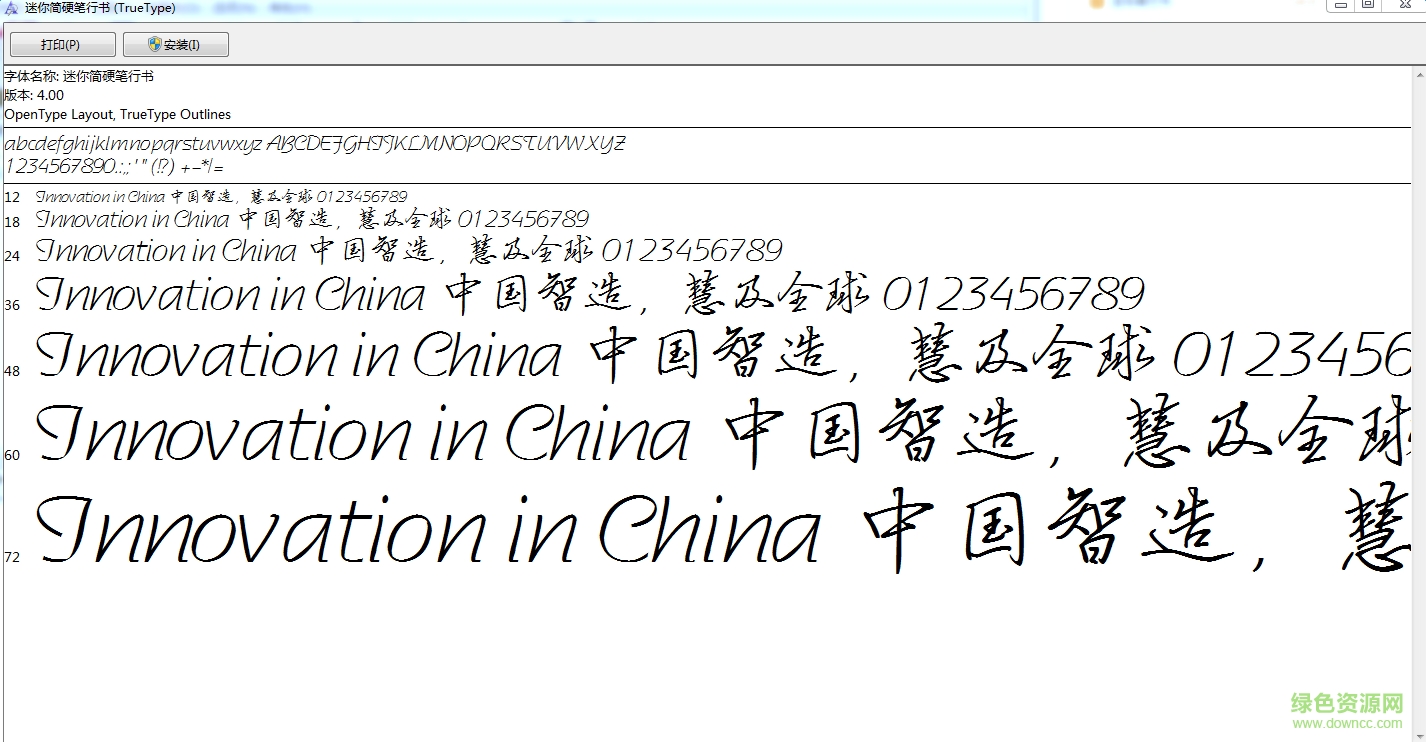
迷你簡(jiǎn)硬筆行書字體是一款行書類字體軟件,其飄逸隨性的風(fēng)格,讓文字栩栩如生,給人一種飛翔的既視感,非常好看,感興趣的朋友歡迎來(lái)綠色資源網(wǎng)體驗(yàn),還有更多字體等你下載哦!
迷你簡(jiǎn)硬筆行書是在楷書的基礎(chǔ)上發(fā)展起源的,介于楷書、草書之間的一種字體,是為了彌補(bǔ)楷書的書寫速度太慢和草書的難于辨認(rèn)而產(chǎn)生的。
字體雋秀工整,結(jié)構(gòu)狹長(zhǎng),字間距較大,排印清晰,整齊
劃一,適用于書籍、報(bào)刊、雜志的標(biāo)題字。
字形見(jiàn)方,結(jié)構(gòu)飽滿,筆法新穎雅致,具有獨(dú)特的藝術(shù)效
果。適用于書籍、報(bào)刊、雜志及宣傳印刷品的標(biāo)題字或裝
飾用字。
字體神采俊俏,雄渾中流露天真稚拙,典雅中蘊(yùn)含時(shí)代風(fēng)
采,靜中寓動(dòng)、穩(wěn)中求險(xiǎn)、巧拙相生、變化自然,結(jié)構(gòu)嚴(yán)
謹(jǐn),筆法古樸典雅,又極富裝飾意趣。適用于書籍、報(bào)
刊、雜志及各類印刷品的標(biāo)題字或裝飾用字。